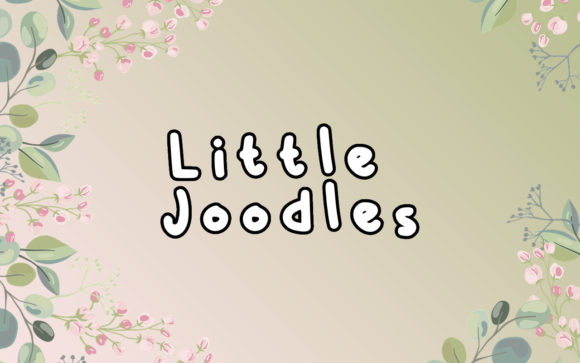
Little Joodles
Việc tìm kiếm các thành phần thiết kế phù hợp có thể là một thách thức, nhưng Little Joodles cung cấp một bộ sưu tập đặc biệt giúp nâng tầm công việc của bạn ngay lập tức.
Được chế tác với độ chính xác cao, Little Joodles cung cấp các vector sạch, kiểu chữ mượt mà và giấy phép thương mại để bạn yên tâm.